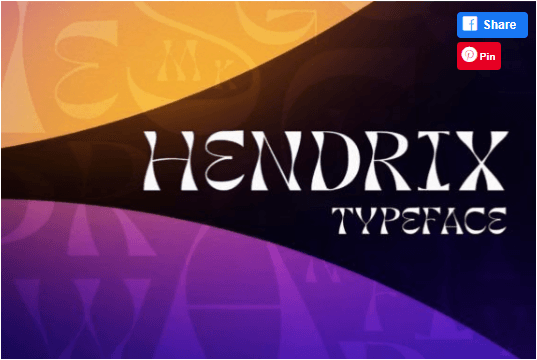
Хендрикс Шрифт
Hendrix Font
Вдохновленный органичным течением ар-нуво, Hendrix представляет собой элегантный, но причудливый дисплейный шрифт. Благодаря своей универсальности его можно использовать для любого проекта.
Hendrix Font
Вдохновленный органичным течением ар-нуво, Hendrix представляет собой элегантный, но причудливый дисплейный шрифт. Благодаря своей универсальности его можно использовать для любого проекта.